HTML의 표준 글꼴을 사용하지 않으려면 Google 글꼴을 사용할 수 있다.
google fonts 사용하기
<head> 섹션에 특수 스타일 시트 링크를 추가한 다음 CSS의 글꼴을 참조하면 된다.
여기서 Google 글꼴의 "Sofia"라는 글꼴을 사용하려고 한다:
여기서 Google 글꼴의 "Triong"이라는 글꼴을 사용하려고 한다:
여기서 Google 글꼴의 "Audiowide"라는 글꼴을 사용하려고 합니다:
다중 구글 폰트 사용하기
여러 Google 글꼴을 사용하려면 다음과 같이 글꼴 이름을 파이프 문자(|)로 구분한다:
참고: 글꼴을 여러 개 요청하면 웹 페이지 속도가 느려질 수 있다! 그러니 그것에 주의하세요.
구글폰트 스타일링
물론 CSS로 구글 폰트를 원하는 대로 스타일링 할 수 있다!
구글 폰트 효과 활성화하기
Google에서는 사용할 수 있는 다양한 글꼴 효과도 사용할 수 있다.
먼저 Google API에 effect= effectname을 추가한 다음 특수 효과를 사용할 요소에 특수 클래스 이름을 추가한다. 클래스 이름은 항상 font-effect-로 시작하고 effect 이름으로 끝난다.
구글 폰트 sofia에 effect를 fire 설정하기 위해 Sofia&effect=fire로 설정하고 font-effect-fire를 class로 설정하면 아래 그림과 같이 sofia 폰트에 불이 난것 같은 효과가 표시된다.
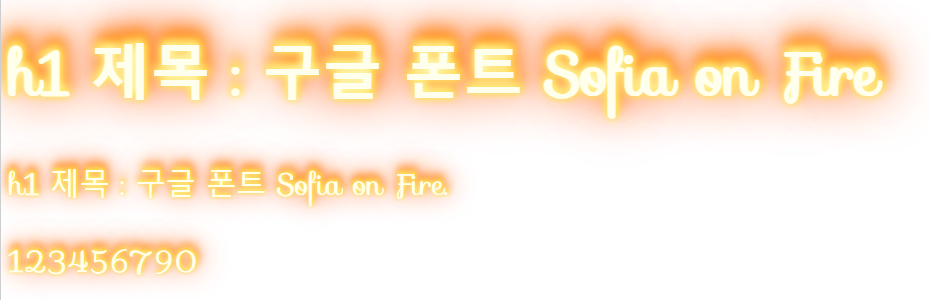
여러 글꼴 효과를 요청하려면 다음과 같이 파이프 문자(|)로 효과 이름을 구분한다:
google fonts에 다양한 효과를 적용한 예시로, neon, outline, emboss, multiple shadow 효과를 적용하였고 결과는 아래 그림과 같다.
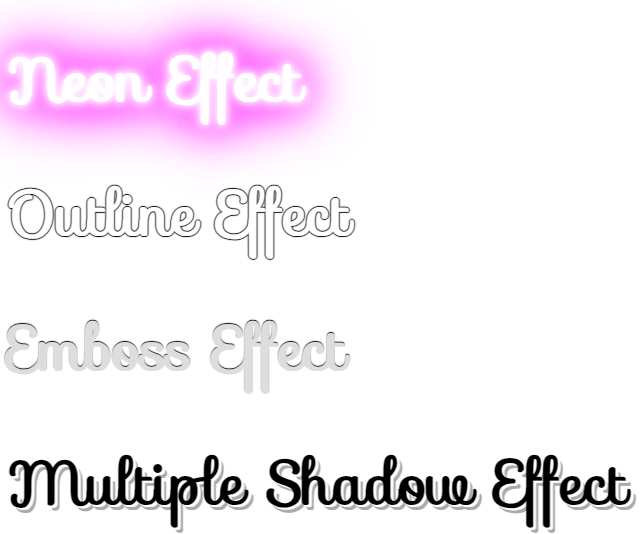
지금가지 CSS에서 google fonts 사용하는 방법과 google fonts에 다양한 효과(neon, emboss, outline, fire 등)를 코드하고 실습해보았다.